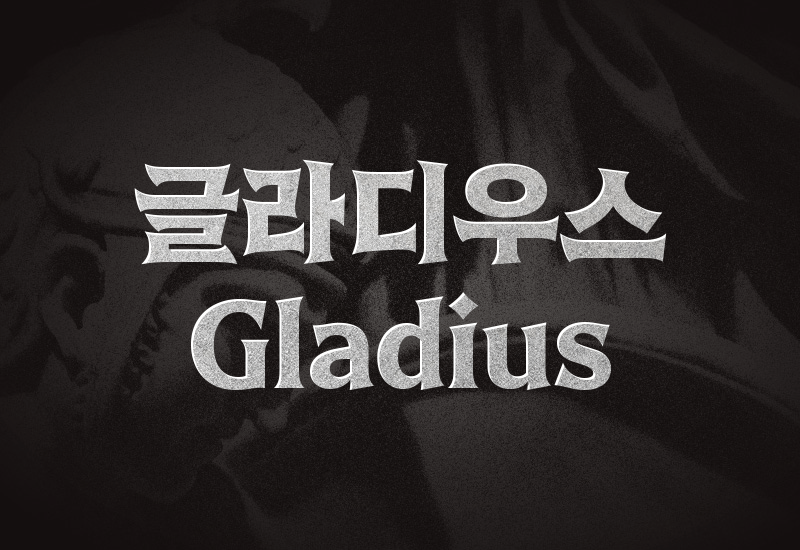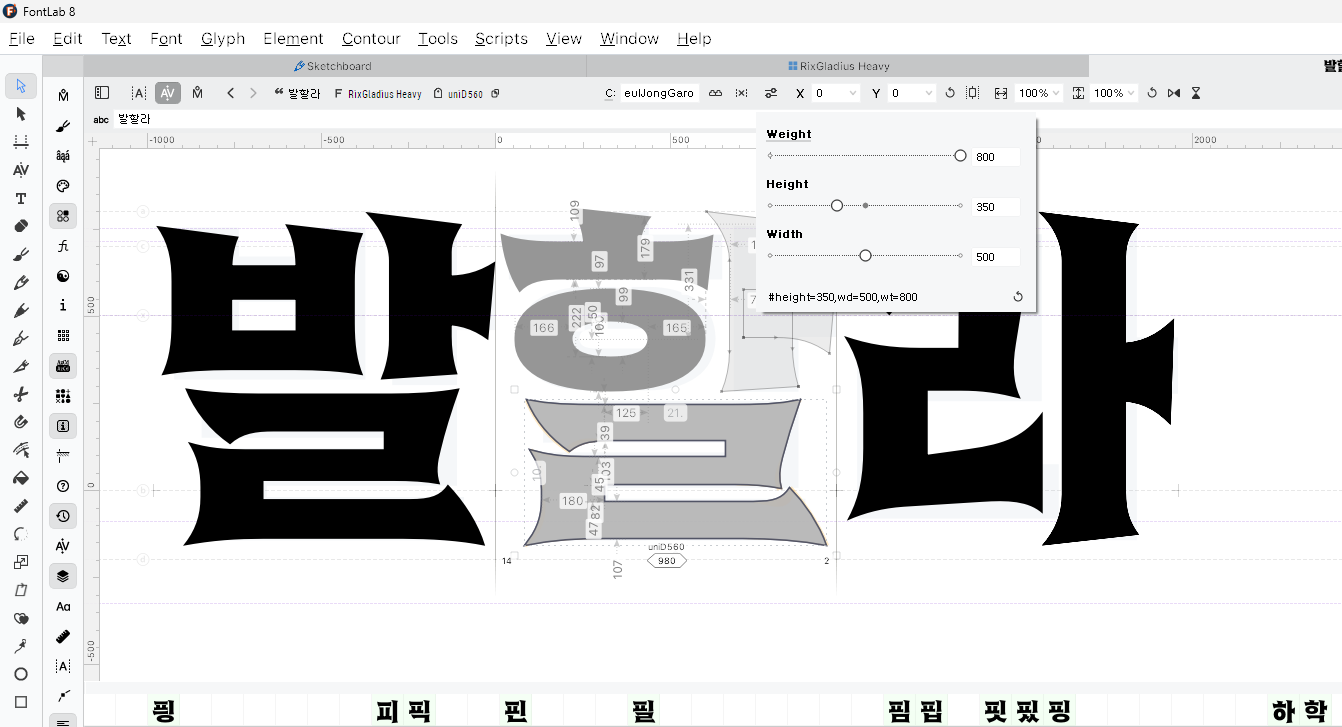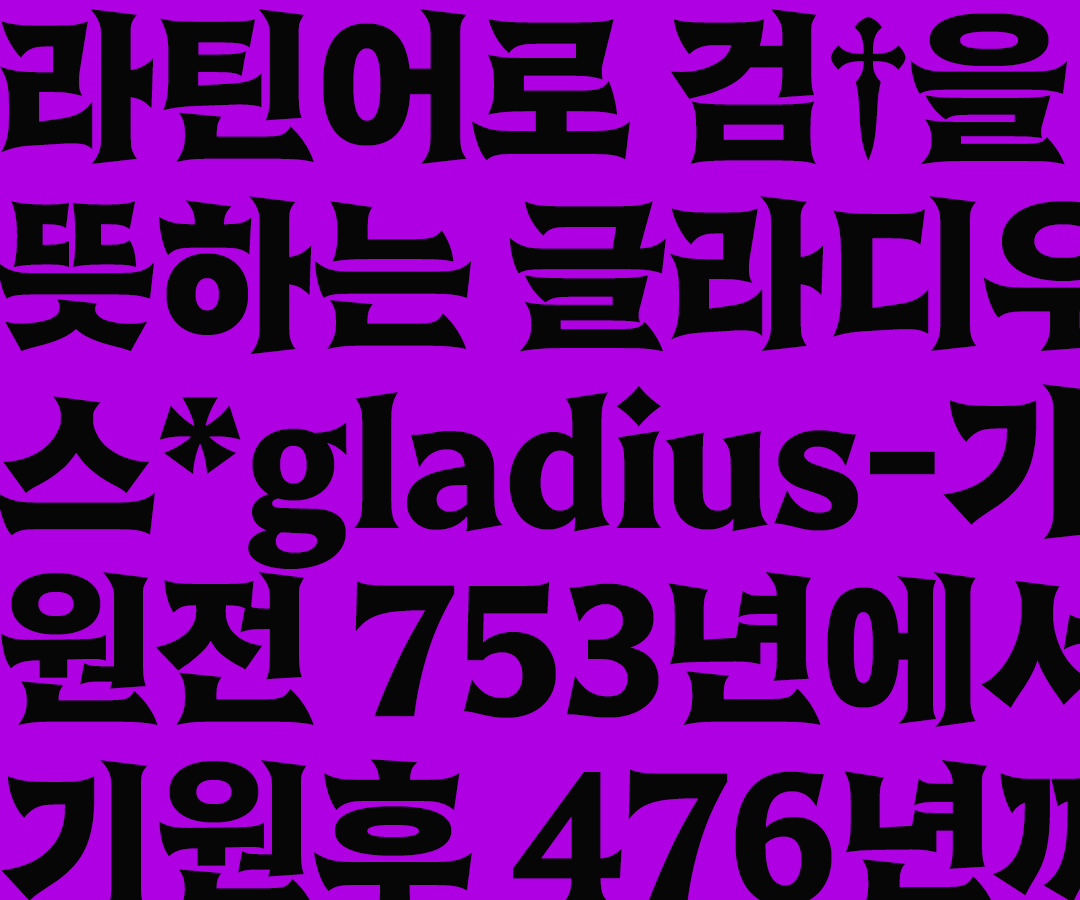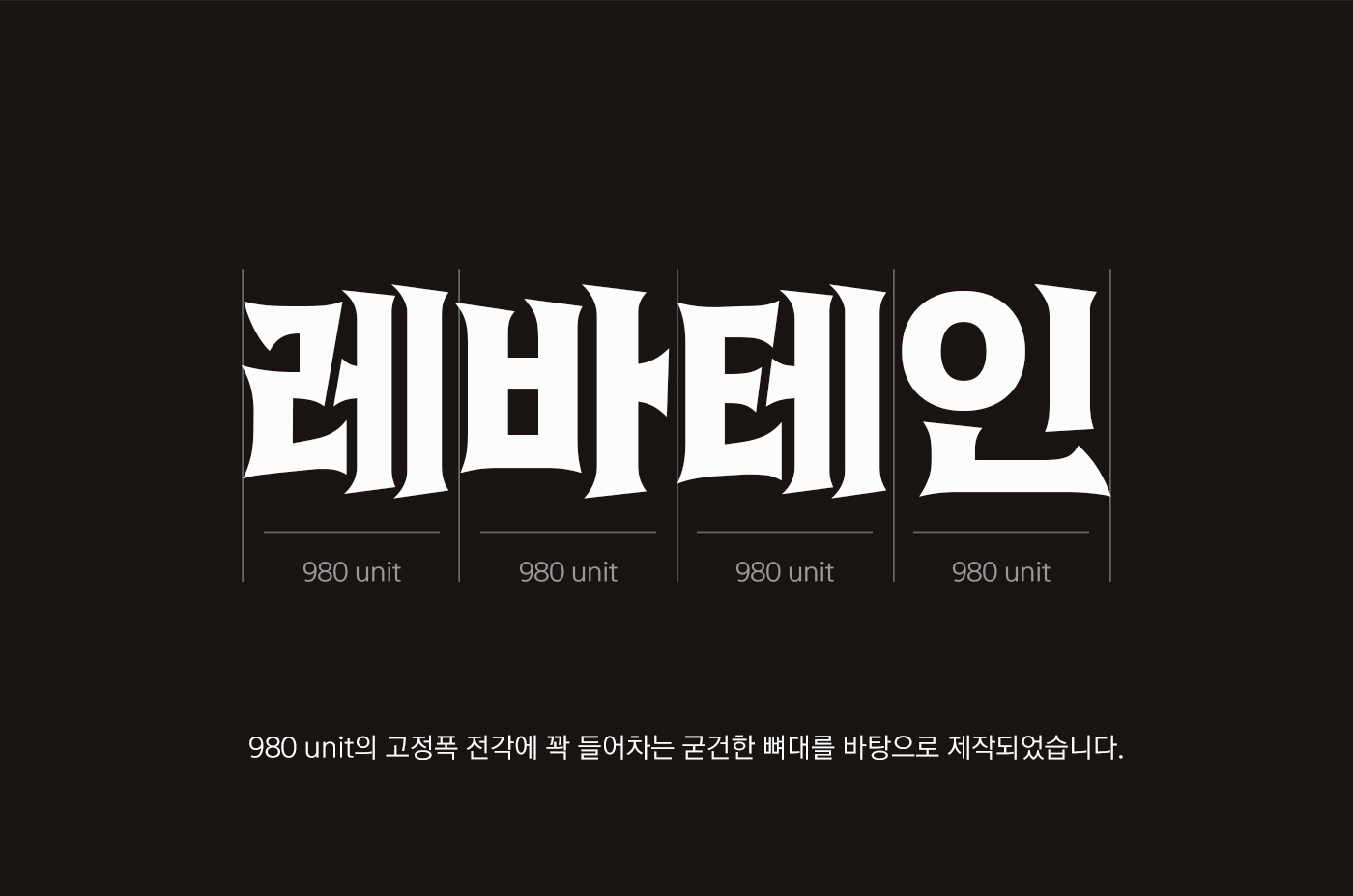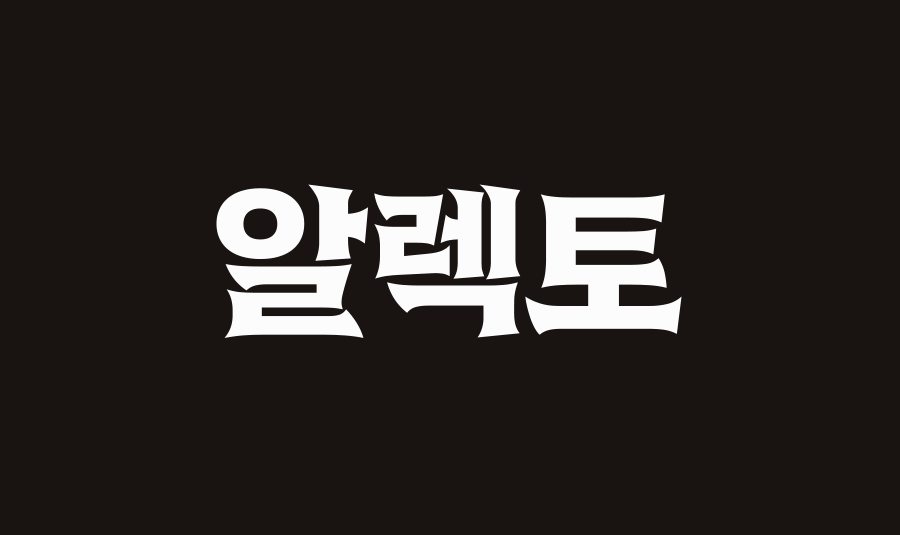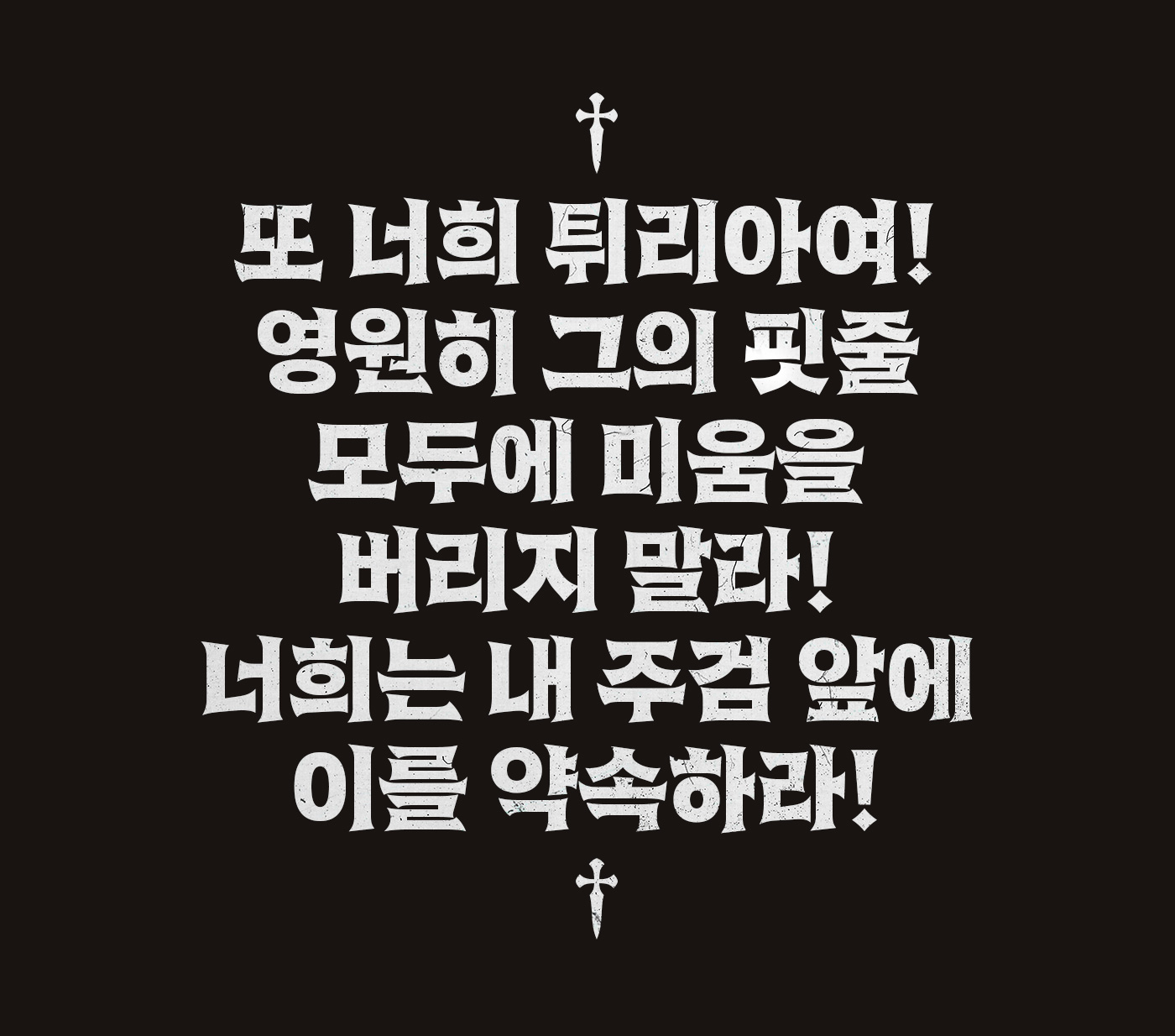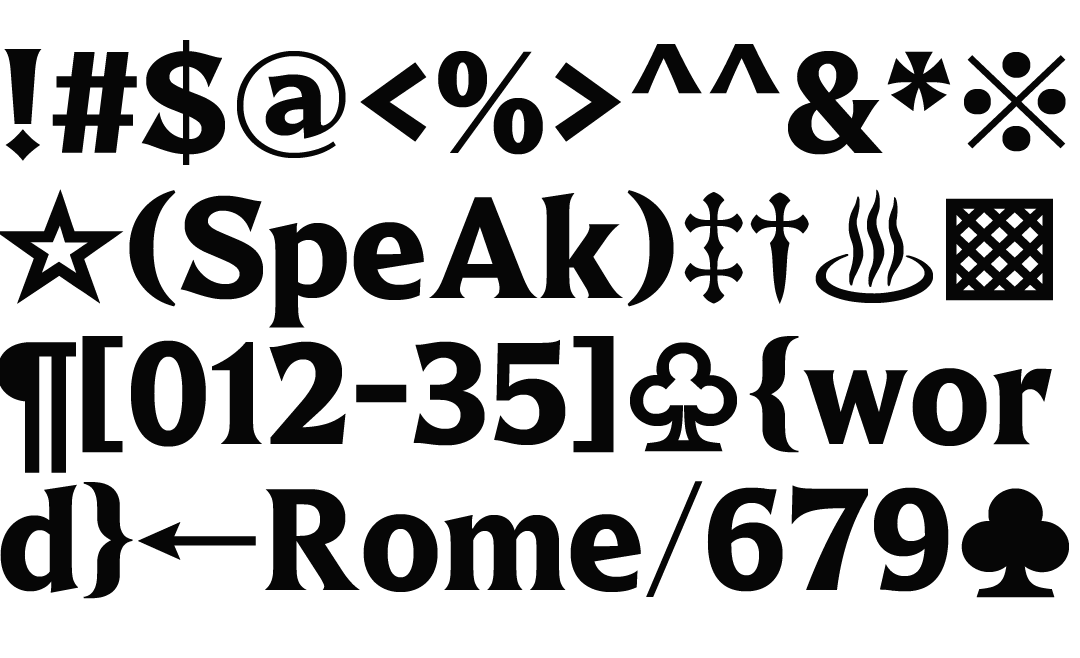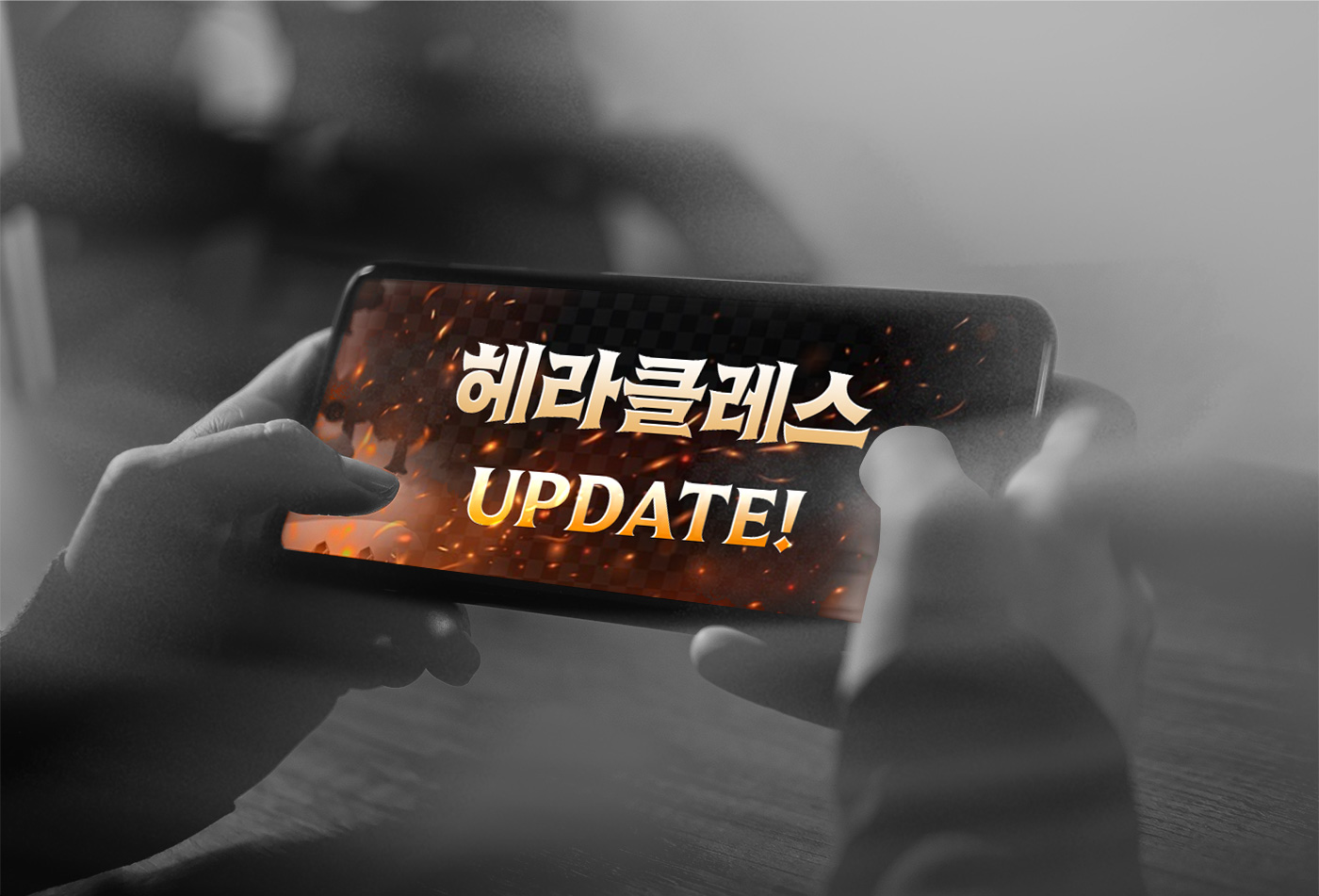
안녕하세요. 오늘은 벌써 2023년 상반기의 마지막 달인 6월의 신규 폰트 「Rix글라디우스」를 소개합니다. Rix앙상블에 이어 또 다른 세리프 서체를 소개하게 되었는데요, 게임 광고에서 튀어나온 듯한 강렬하고 날카로운 형태가 눈에 띄는 폰트입니다. 이번 서체를 기획하고 제작한 박민우 디자이너를 인터뷰를 통해 만나보겠습니다 :)
서체명이 디자인과 참 잘 어울리는데, 어디에서 영감을 받았고 어떻게 기획하게 되었는지 궁금해요.
Rix글라디우스는 트라야누스 비문 글자와 같은 로마 명각 글자에서 영감을 받아서 시작한 작업입니다. 한글에 맞춰 구조는 조금 달라졌지만, 글리픽 스타일* 대문자의 플레어 세리프와 넓고 시원시원하게 뻗은 골격 등을 참고해 서체를 제작하게 되었습니다. 날카롭고 단단한 미감의 특징을 살려, 로마 제국 시절 군인들이 쓰던 검의 이름을 따 글라디우스라는 이름을 붙이게 되었답니다. 이름에 맞춰, 대거 †(0x2020) 글립의 대체 형태로 글라디우스 모양을 추가했답니다.
*글리픽 스타일
돌이나 동판 위에 새겨진 글자체 양식
제작을 하면서 어려웠던 점이나 특히 더 신경을 쓴 부분이 있다면?
뾰족하게 뻗는 획 끝을 특징으로 하다 보니 자소의 디테일을 살리며 공간을 분배하기가 어려웠습니다. 쌍시옷, 쌍지읒의 내리점과 삐침이 가운데 만나는 지점 등이 골치 아프더라고요. 시간을 많이 쏟았답니다!😂 또한 이번 작업에는 폰트랩 8의 스마트 배리어블 컴포넌트 기능을 사용했어요. 설정한 축에 따라 폰트의 외형을 변경할 수 있는 배리어블 폰트와 같이 글립 하나하나마다 축을 설정해 컴포넌트로 불러왔을 때 모양을 바꿀 수 있는 기능인데요, 비슷한 꼴 글립의 자소 디자인이 일관성을 가지게 하기 위해 도움을 많이 받았습니다.
서체의 인상이 굉장히 강렬한데, 어떻게 활용하면 좋을까요?
전각에 꽉 들어찬 공격적인 얼굴을 가지고 있는 서체라서, 강렬한 메시지를 전달하길 원하실 때 사용하기 좋을 것 같아요. 고대~중세 전쟁 배경의 판타지 게임이나 소설 등의 타이틀에 사용하시면 어떨까 싶습니다.
앞으로 하고 싶은 작업은?
이번 작업으로 사납고 화려한 표정의 글자는 익숙해져서요, 이제는 동글동글 귀엽고 뭉툭한 서체도 작업해 보고 싶은 마음이 생겼습니다! 금방 또 신서체로 찾아뵐 테니까 조금만 기다려 주세요!
단단하고 날카로운 글자🗡️
첫눈에 강렬한 인상이 강하게 느껴지는 Rix글라디우스는 날카로운 검과 같이 획의 끝단이 넓게 벌어지는 독특한 세리프가 특징입니다. 위 인터뷰에서도 이야기했듯 고대 로마 시대의 비문*에 새겨진 글자에서 영감을 받아 제작하게 된 폰트입니다.
*비문 epitaph
묘비에 새겨진 글
고정폭의 비교적 넓은 글자 너비로 네모꼴에 꽉 차는 형태이며, 곧고 단단한 뼈대가 안정감 있게 잡아줍니다.
바깥쪽으로 날카롭게 빠지는 획 처리는 고대 로마에서 사용하던 검의 형상을 더욱 떠오르게 하는데요. 단어로 모였을 때 전체적으로 뾰족한 실루엣의 덩어리를 형성해 더욱 역동적이고 힘 있는 이미지가 느껴집니다.
더 넓어진 라틴 확장⚔️
라틴 94자 외 라틴 확장 178자와 숫자, 약물 등에도 같은 특징을 적용하여 여러 문자를 섞어 써도 이질감이 없도록 개발했습니다. 영문, 숫자, 특수기호 디자인에도 넓게 퍼지는 세리프와 작은 획 대비로 일관된 인상을 주도록 디자인했습니다.
이렇게 활용해 보세요📌
시선을 확 사로잡는 서체 디자인으로 게임 광고에 특히 잘 어울리는 것 같아요. 그래픽적인 요소와의 조합도 좋아 로고나 포스터, 도서 등 콘텐츠에 힘 있게 메시지를 전달해야 할 때 활용하기 좋습니다.